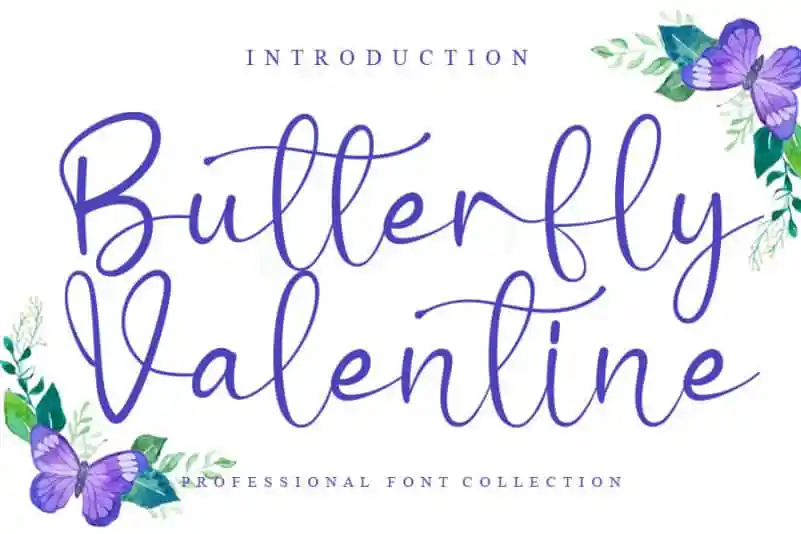
Butterfly Valentine Calligraphy Font – Download Grátis
Descubra a espiritualidade das palavras com Butterfly Valentine Calligraphy Font. Esta fonte é ideal para quem busca uma experiência única na escrita manual, trazendo vida e emoção aos seus projetos digitais. Com uma design minimalista mas repleto de detalhes, essa fonte é perfeita para criar mensagens sutis, como cartas personalizadas ou enfeites de papel para eventos especiais. A Butterfly Valentine Calligraphy Font foi criada pelo Designer creativeletter e carrega um ar de sofisticação que se torna uma peça chave em qualquer projeto gráfico. Suas linhas suaves e elegantes são perfeitamente adaptáveis para diferentes estilos, desde a escrita tradicional até as mais modernas abordagens digitais. Para quem procura adicionar um toque único a suas criações digitais, essa fonte é definitivamente uma opção a ser considerada. Seja para criar cartões de aniversário, enfeites de papel ou qualquer outro projeto que exigirá um pouco de carinho e cuidado na escrita manual, Butterfly Valentine Calligraphy Font trará ao seu trabalho um toque especial. Com sua capacidade única de tornar cada palavra uma obra-prima, esta fonte é um must-have para designers apaixonados por um estilo clássico revivido. Seja ele aprimorado ou simples, ela complementará perfeitamente qualquer projeto em que você estiver trabalhando.